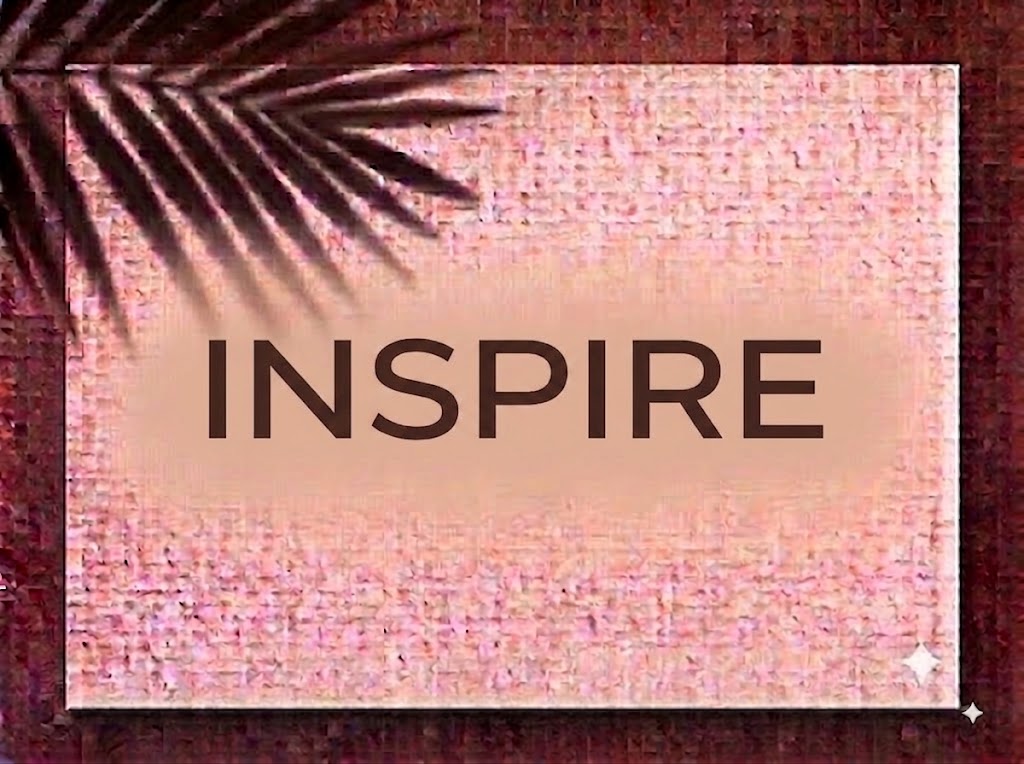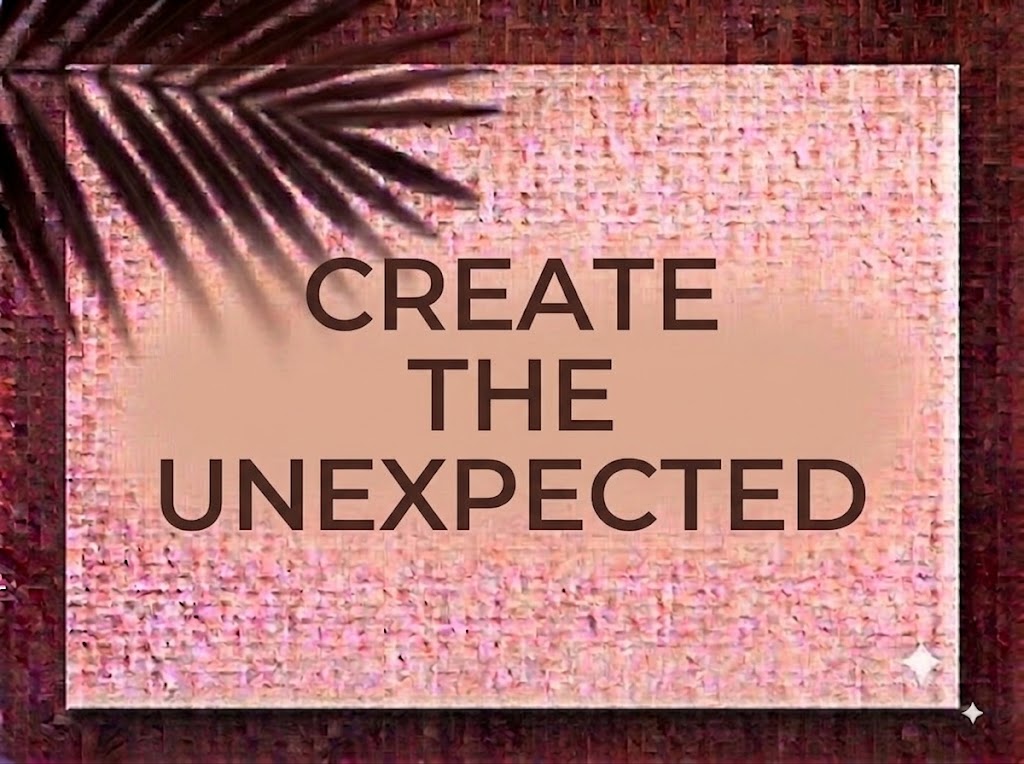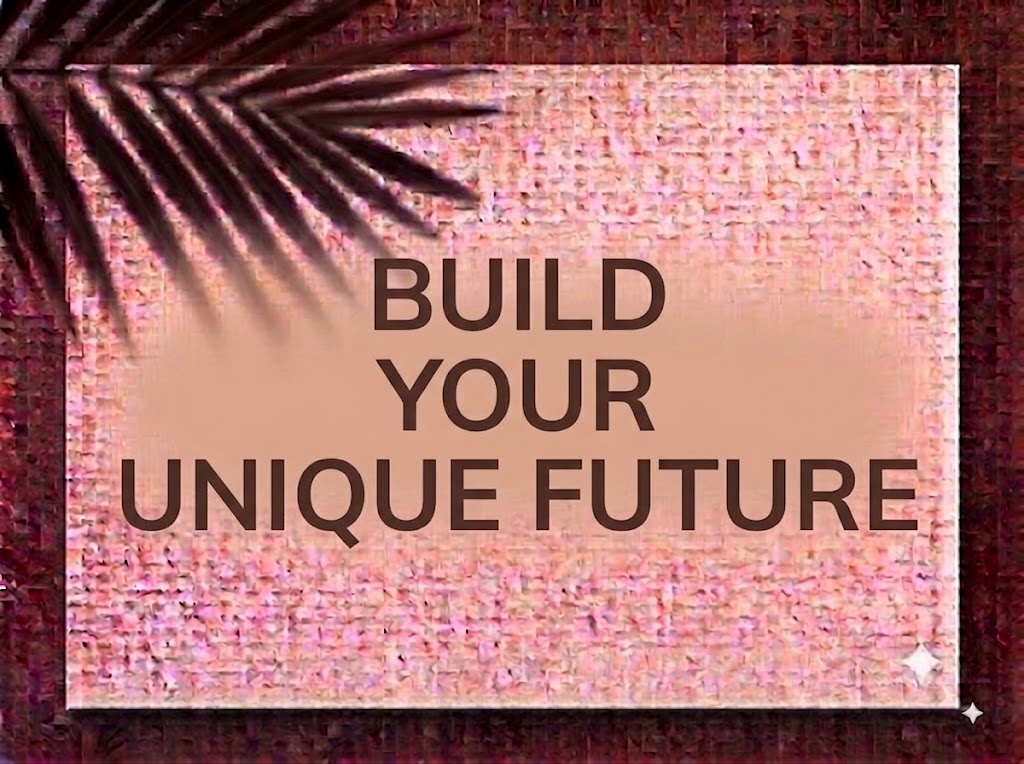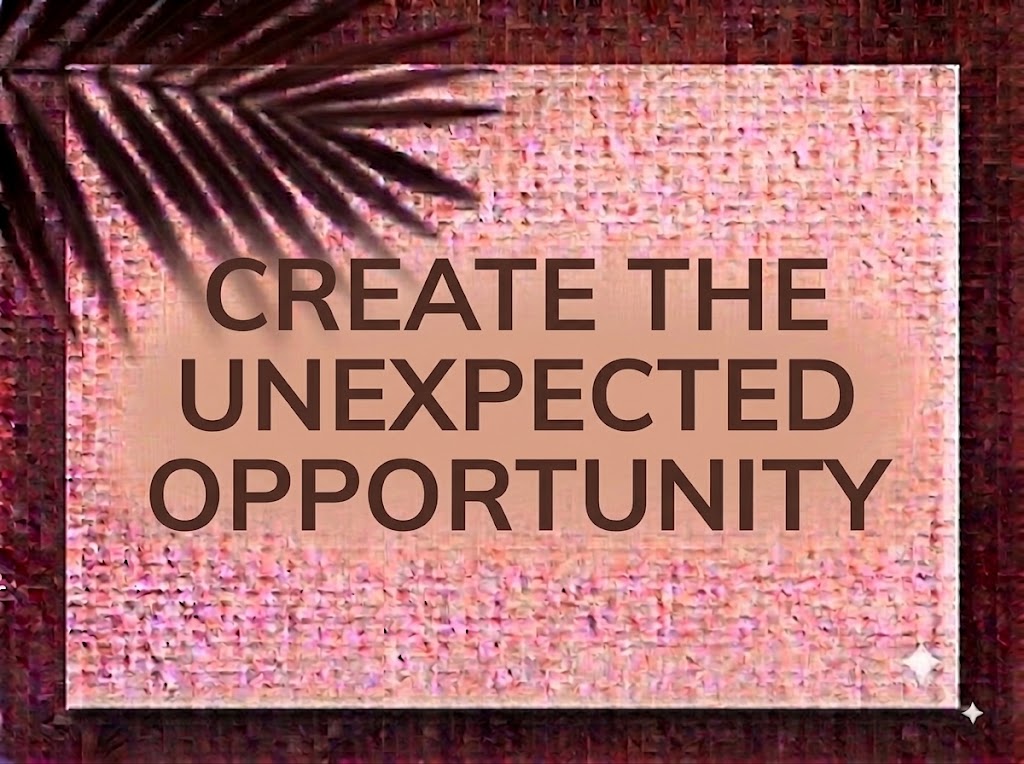
1FTV VIP Bregan
Trong xu hướng thiết kế đồ họa và nhận diện thương hiệu đương đại, các bộ phông chữ không chân hình học (Geometric Sans-Serif) mang phom dáng mở rộng, đường nét bo cong mềm mại luôn giữ vị trí độc tôn. Sự kết hợp giữa cấu trúc tối giản và tỷ lệ chữ cân đối mang đến cảm giác hiện đại, công nghệ, thân thiện nhưng không kém phần đẳng cấp cho mọi ấn phẩm truyền thông.
Nếu bạn đang tìm kiếm một phông chữ Sans-Serif thời thượng, tinh gọn để làm nhận diện thương hiệu công nghệ, thiết kế giao diện (UI/UX), bao bì sản phẩm hay tiêu đề video ngắn, font 1FTV VIP Bregan chính là sự lựa chọn không thể bỏ qua.
Giới thiệu về font 1FTV VIP Bregan
Font 1FTV VIP Bregan là bộ chữ không chân mang phong cách Geometric Sans-Serif hiện đại, kết hợp khéo léo giữa cấu trúc hình học chuẩn mực và các đường cong mềm mại:
Tên phông chữ: 1FTV VIP Bregan
Được hoàn thiện kỹ lưỡng về mặt kỹ thuật, 1FTV VIP Bregan đem lại khả năng hiển thị vô cùng sắc nét trên cả màn hình kỹ thuật số độ phân giải cao lẫn các ấn phẩm in ấn thương mại. Bạn có thể tự tin phóng lớn chữ trên Photoshop, Illustrator hay Premiere mà không lo bị vỡ nét hay nhòe đường biên.
Đặc điểm nổi bật của phong cách thiết kế VIP Bregan
Sức hút thị giác của font 1FTV VIP Bregan đến từ sự tinh giản tối đa cùng cấu trúc chữ tròn đầy, phóng khoáng:
Cấu trúc hình học bo tròn mềm mại: Các ký tự như
o,e,c,a,d,b,gđược tạo hình với các đường cong mở rộng mượt mà, tạo cảm giác thân thiện, nhẹ nhàng và giàu tính tương lai (futuristic/modernist). -
Tỷ lệ khung chữ rộng thoáng: Phom dáng chữ có xu hướng nở nhẹ về chiều ngang (extended touch), giúp các dòng tiêu đề đứng vững chãi trên bố cục, tạo nhịp điệu đọc vô cùng dễ chịu và thông thoáng.
Độ dày nét đồng đều (Monoline): Nét chữ liền mạch với tỷ lệ tương phản cực thấp giúp chữ luôn giữ được độ rõ ràng, sắc nét kể cả khi hiển thị ở kích thước nhỏ hoặc đặt trên các background đa sắc màu.
Khoảng cách giữa các chữ (kerning) và tracking được tính toán cân bằng, đảm bảo các khối văn bản dài không bị dính nét hay rời rạc.
Tích hợp trọn vẹn bộ chữ cái hoa – thường, dãy chữ số 0-9 phom dáng hiện đại cùng hệ thống ký tự đặc biệt, dấu câu thông dụng.
Bản Việt hóa chuẩn chỉnh từ fonttiengviet.com với hệ thống dấu tiếng Việt (sắc, huyền, hỏi, ngã, nặng, mũ, móc) được trau chuốt tinh gọn, đặt đúng trọng tâm thị giác, không làm ảnh hưởng đến độ giãn dòng khi soạn thảo.
Hình ảnh demo thực tế của font 1FTV VIP Bregan
Khả năng hiển thị của phông chữ này được tối ưu rất tốt trên nhiều tỷ lệ kích thước khác nhau:
Kích thước nhỏ (12pt – 24pt): Cấu trúc chữ mở rộng giúp các đoạn văn bản tiếng Việt và dãy số hiển thị rành mạch, cực kỳ dễ đọc trên màn hình di động.
Kích thước lớn (36pt – 72pt): Đây là đất diễn lý tưởng nhất để 1FTV VIP Bregan phô diễn toàn bộ vẻ đẹp tối giản, hiện đại và tinh tế của các đường cong bo tròn, tạo tác động thị giác mạnh mẽ cho các dòng headline chính.
Ứng dụng trong thiết kế đồ họa và làm video
Sở hữu nét cá tính tối giản và linh hoạt, font 1FTV VIP Bregan mở ra không gian ứng dụng phong phú:
Video ngắn (TikTok, Reels, Shorts): Dáng chữ không chân hiện đại hiển thị rất rõ ràng trên khung hình đứng tỷ lệ 9:16. Cực kỳ ăn nhập với các video vlog đời sống, review công nghệ, kiến trúc, nội thất, podcast hay hướng dẫn kỹ thuật.
Ảnh thu nhỏ YouTube (Thumbnail): Lựa chọn tuyệt vời cho các kênh làm nội dung về Tech, Setup góc làm việc, AI, Tài chính hay Phong cách sống tối giản (Minimalism) nhờ giao diện chuyên nghiệp và thu hút.
Nhận diện thương hiệu & UI/UX Design: Hoàn hảo để thiết kế logo dạng chữ, banner website, ứng dụng di động cho các công ty khởi nghiệp công nghệ, agency sáng tạo, studio kiến trúc hay nhãn hàng thời trang hiện đại.
Thiết kế Bao bì & Poster: Thích hợp làm nhãn mác mỹ phẩm organic, đồ uống cao cấp, bao bì thiết bị thông minh và poster sự kiện triển lãm.